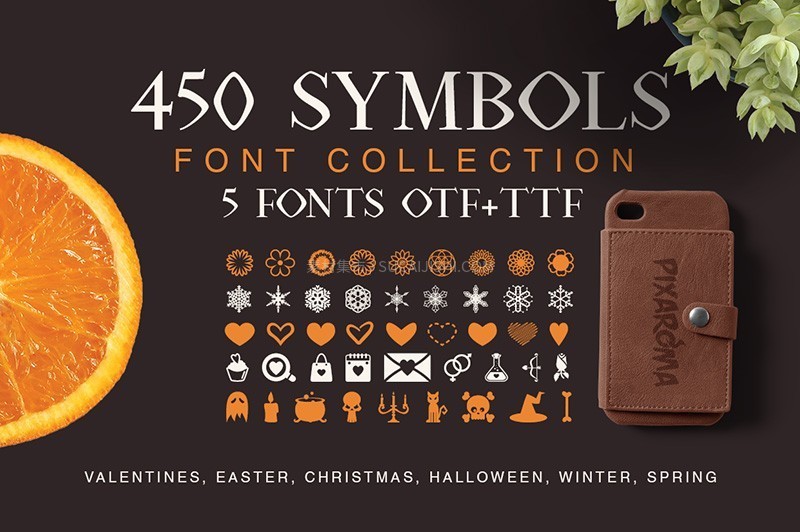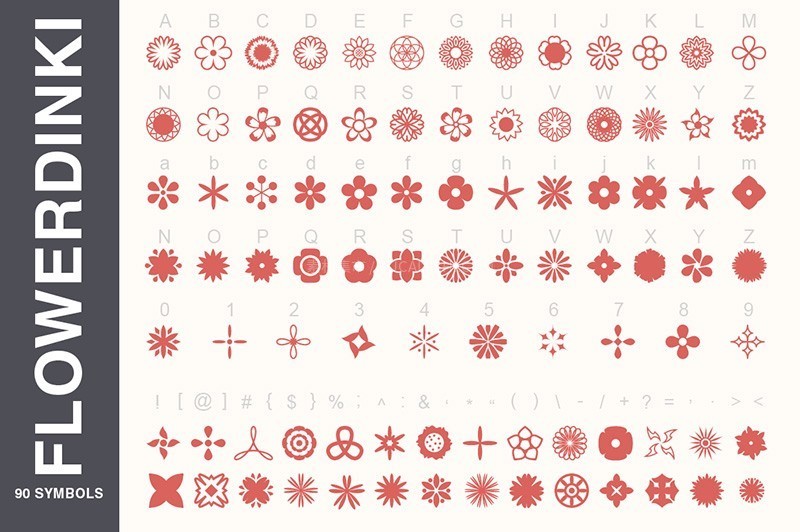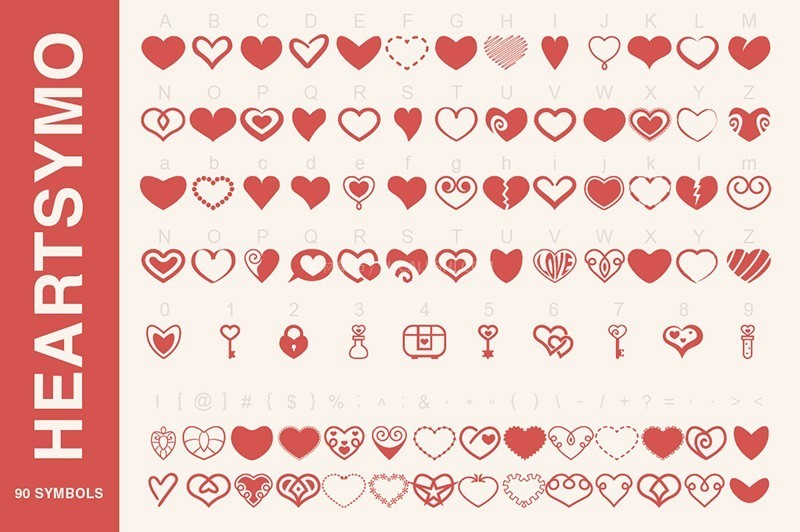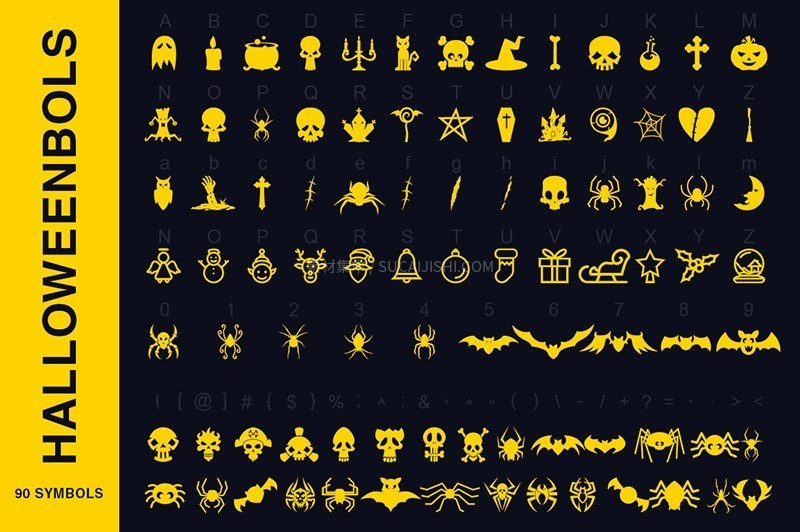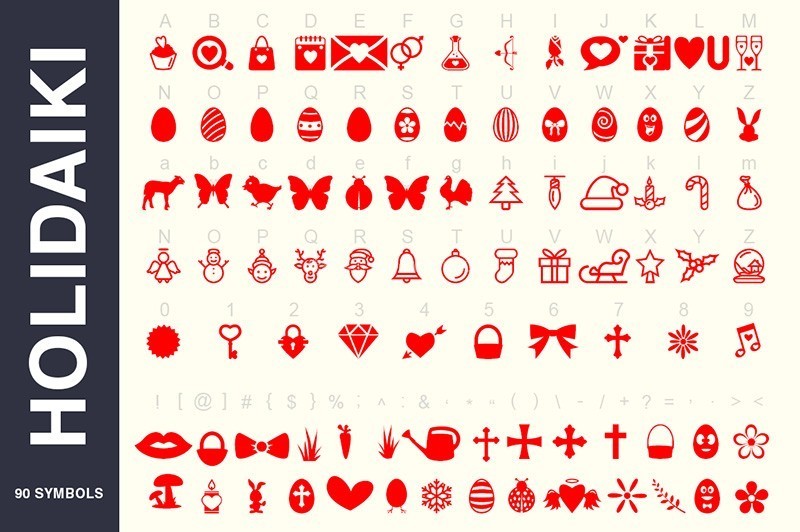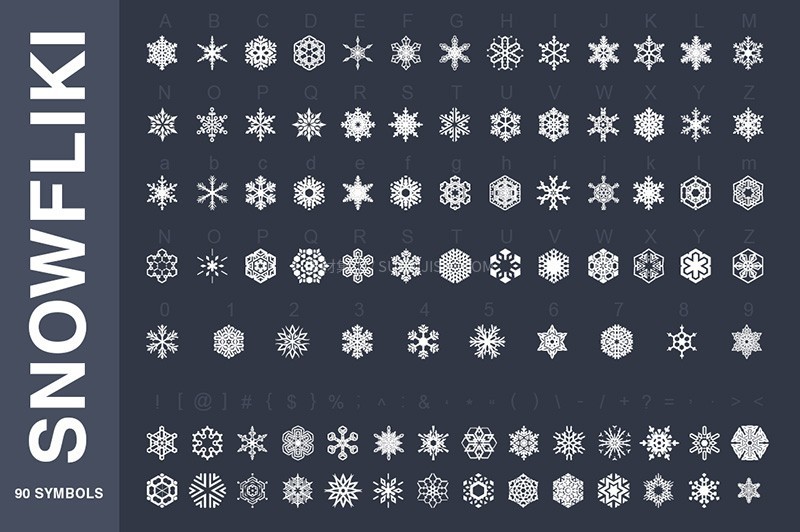
这套庞大的符号字体集合,内含 5 款独特字体和超过 450 种图形符号。不同于传统素材,这些符号以字体形式存在,每个符号都对应一个键盘字母或字符,让您无需导入图片,只需像打字一样输入字母即可在任何设计或文案软件中调用。涵盖心形、花卉、万圣节、雪花和通用节日元素,助您轻松为设计项目增添独特的手绘质感和高效的装饰效果。